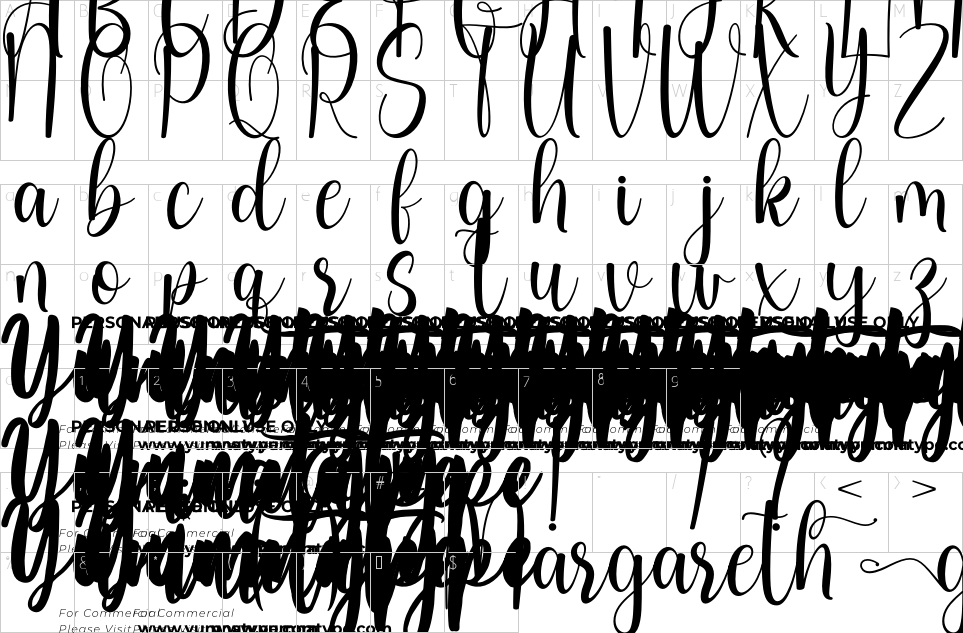
A fonte Margareth Gretal é uma escolha perfeita para designers que buscam uma variedade de linhas elegantes e modernas. Desenhada pela incrível equipe do Yumna Type, ela oferece uma grande versatilidade para várias aplicações, desde sites profissionais até editoriais de revistas. Com mais de 1.600 downloads, Margareth Gretal já foi usada por designers de todo o mundo para adicionar um toque único a seus projetos. Essa fonte é uma excelente opção para designers que valorizam um design minimalista e sofisticado, que se adapta perfeitamente a várias tamanhos de texto e estilos de design. Se você está procurando por uma fonte única e versátil para seu próximo projeto, Margareth Gretal é uma escolha atraente que merece ser considerada.